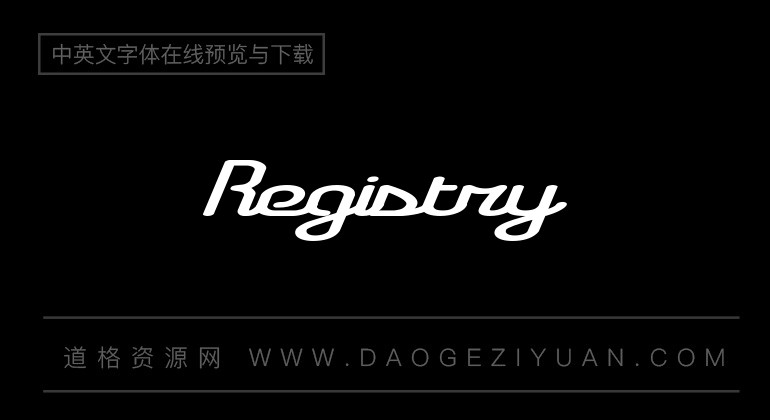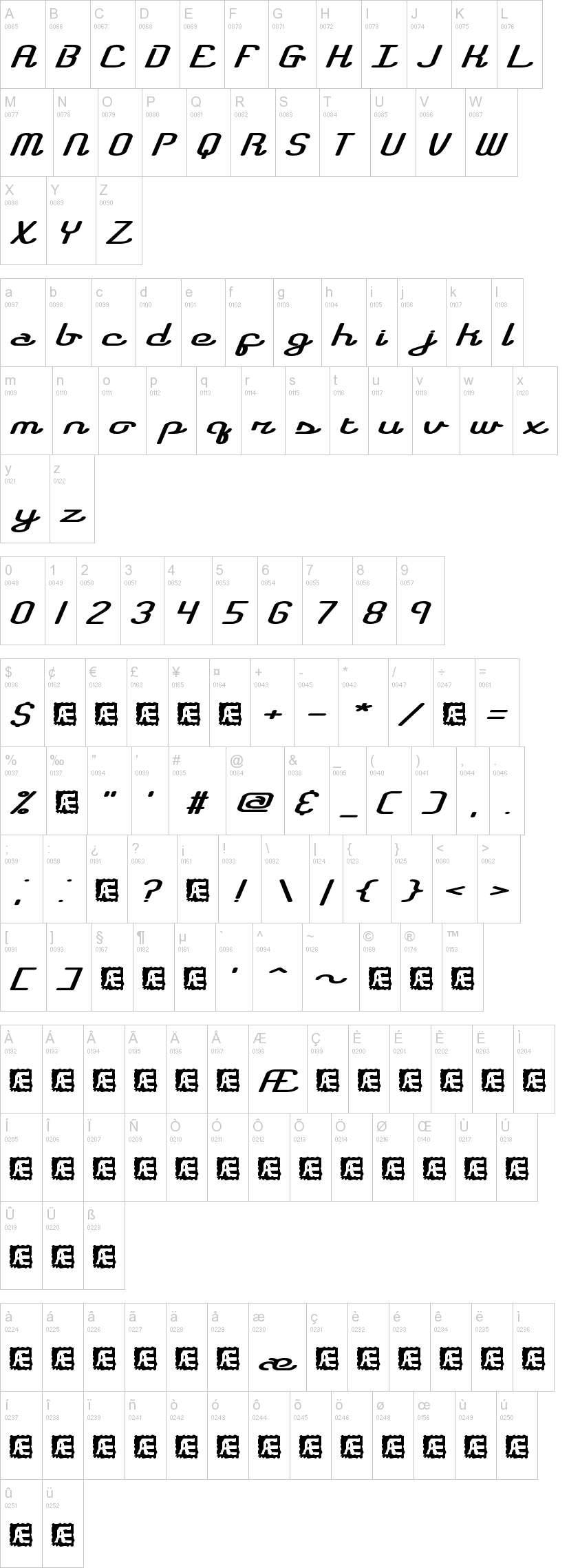
Registry
Registry 字体是一种由 Microsoft Corporation 开发的 TrueType 字体。该字体是在 Windows 操作系统中预安装的,可用于在各种应用程序中进行文本编辑和显示。 Registry 字体具有清晰的线条和现代的外观,适用于各种用途,包括电子邮件、文档、电子书、网页设计等。它还具有良好的可读性和易于识别的特点,使其成为一种受欢迎的字体选择。 Registry 字体拥有多种不同的字重和样式,包括正常、粗体、斜体和粗斜体,适合不同的设计需求。此外,该字体还支持多种语言和字符集,包括英语、西班牙语、法语、德语等等。 总的来说,Registry 字体是一种实用的、易于使用和通用的字体,适合许多应用场景。
Registry是一款非常不错的手写艺术字体,具有很好的视觉感,适合于文化类的宣传设计、商业类品牌的广告和产品包装设计以及个性化文字排版等较多场景。
Registry字符映射图